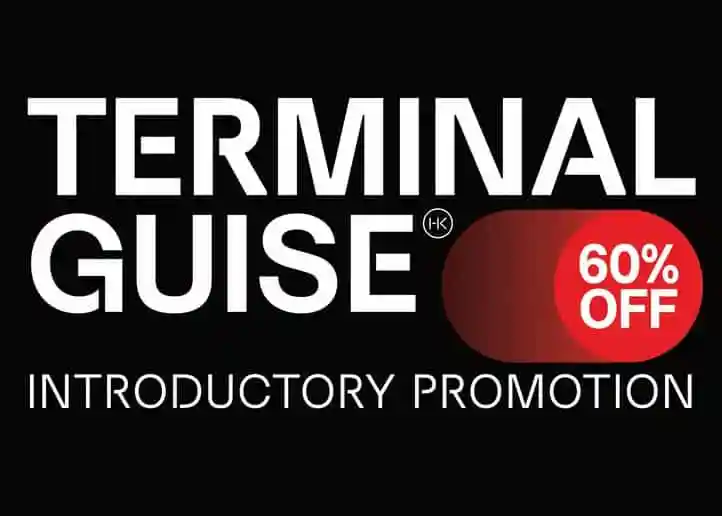
Terminal Guise Sans Serif é uma elegante fonte geométrica sem serif que traz consigo uma sensação tecnológica forte e formas modernas e alegres, ideal para qualquer projeto imaginável. Suas linhas diretas e formas desfeitas criam um encadeamento gracioso e estilizado, tornando-a perfeitamente adaptável para aplicações de mídia exibição. Designado pelo font designer Hanken Design Co., é uma tipografia para exibição com formas dissociadas ou incompletas que oferecem ao usuário a possibilidade de finalizar as impressões de forma artística e estilizada, tornando-a uma opção ótima tanto para aplicações corporativas quanto para criações digitais modernas. Com suas linhas aguçadas e formas sóbrias, Terminal Guise Sans Serif é certamente um recurso gráfico indispensável no seu armário de fontes.